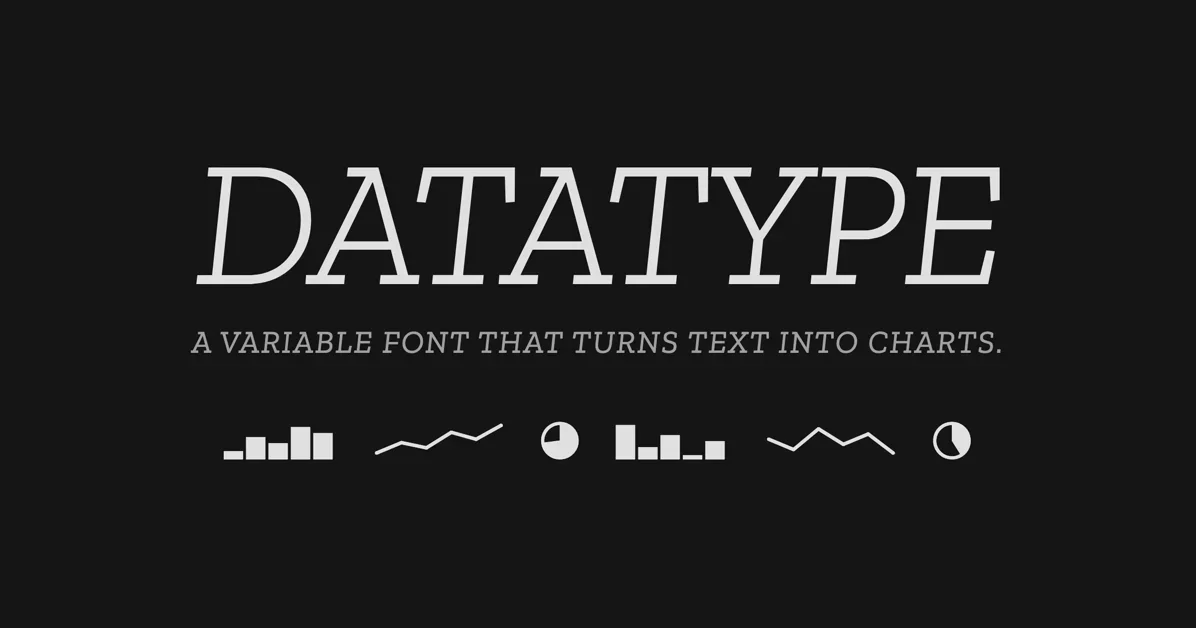
텍스트가 차트로 변신하는 마법, Datatype 등장!
Datatype은 텍스트 문법을 이용해 인라인 차트를 생성하는 혁신적인 변수 폰트(Variable Font)임
별도의 JavaScript나 렌더링 라이브러리 없이 타이포그래피(Typography) 자체로 시각화 구현
접근성 문제와 실제 사용성에 대한 커뮤니티의 우려가 제기됨
CSS 통합으로 웹 어디서든 텍스트처럼 차트 삽입 가능
변수 폰트(Variable Font) 기반 차트 렌더링
Datatype은 OpenType 변수 폰트(Variable Font) 기술을 활용하여 텍스트 자체를 차트로 렌더링합니다. 두 개의 축(Axes)을 통해 차트의 밀도와 두께를 조절할 수 있으며, 이는 CSS의 font-variation-settings 속성을 통해 제어됩니다. 개발자는 별도의 렌더링 엔진 없이 HTML 내에서 특정 문법을 타이핑하는 것만으로 차트를 구현할 수 있다는 점이 주목할 만합니다.
접근성(Accessibility) 및 사용성 논쟁
커뮤니티에서는 Datatype의 접근성(Accessibility)에 대한 심각한 우려가 제기되었습니다. 폰트 파일 로딩 실패 시 내용이 보이지 않는 문제, 스크린 리더가 텍스트 기반 차트 값을 제대로 해석하지 못할 가능성 등이 지적되었습니다. 또한, 일부 브라우저 확장 프로그램(uBlock Origin 등)이 폰트 파일을 차단하여 초기 렌더링에 실패하는 사례가 보고되어, 실제 환경에서의 안정적인 사용성에 대한 의문이 제기되었습니다.
CSS 통합 및 적용 방식
Datatype은 CSS `@font-face` 규칙과 `font-family` 설정을 통해 웹사이트에 쉽게 통합됩니다. `font-variation-settings`를 이용해 너비(width)와 두께(weight)를 조절하며, 텍스트 내에서 차트 표현을 위해 리거처(Ligature) 치환 기능을 활용합니다. 이는 기존 텍스트 렌더링 파이프라인을 그대로 사용하므로, 테이블, 대시보드, 보고서 등 텍스트가 사용되는 모든 곳에 자연스럽게 적용될 수 있다는 장점이 있습니다.
데이터 시각화 방식의 한계
텍스트 기반 차트라는 접근 방식은 데이터의 시각적 표현을 간결하게 제공하지만, 복잡한 데이터 분석이나 상호작용에는 한계가 있다는 의견이 있습니다. 제공된 값들이 0-100 사이의 백분율로 표현되는 점, 그리고 텍스트 자체로만 차트 값을 파악하는 것이 일반적인 사용자 경험과 다르다는 점이 지적되었습니다. 따라서 정보 전달의 명확성과 사용자 기대치 사이의 균형이 중요할 것으로 보입니다.